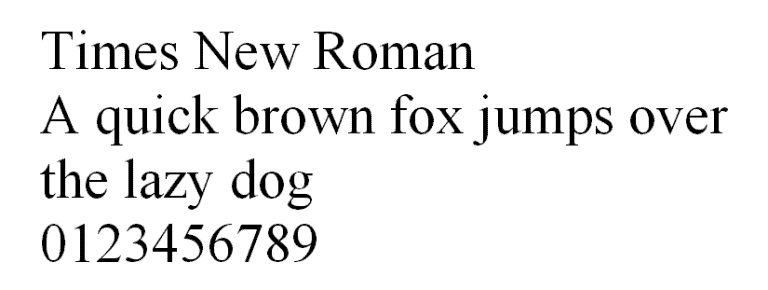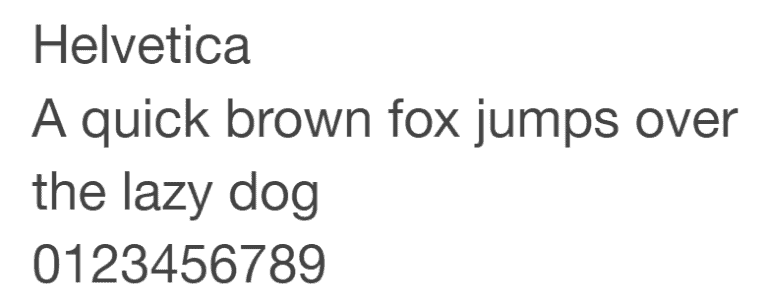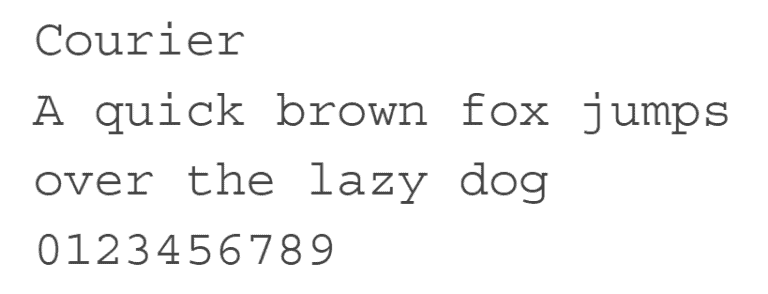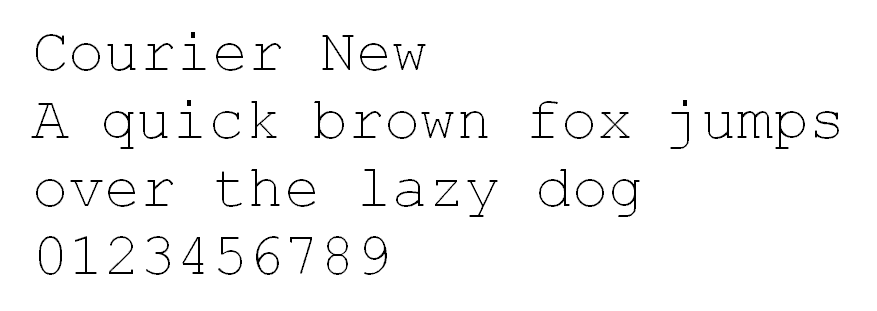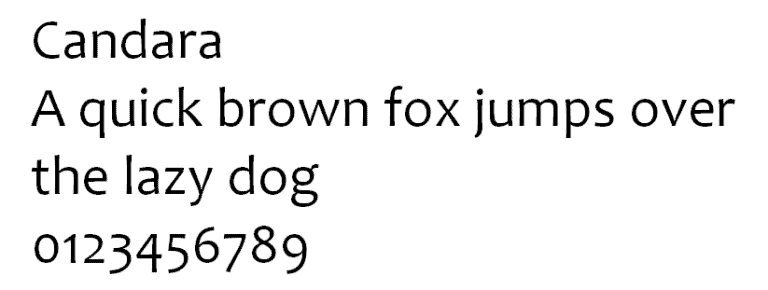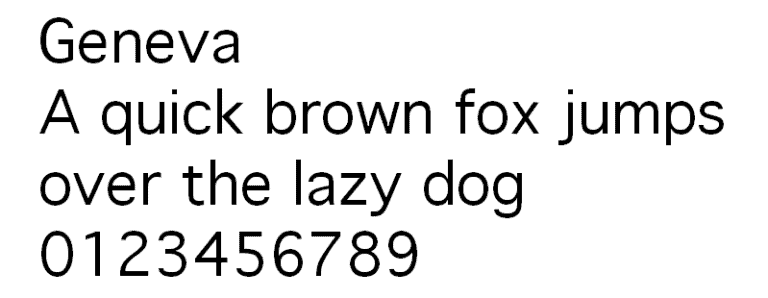
I 20 migliori font HTML da usare nel 2026
I font svolgono un ruolo importante nell’appeal visivo complessivo di un sito web. Un font scelto con cura aiuta a trasmettere il giusto messaggio e a stabilire la coerenza del brand.
A tal fine, un ottimo font per il web deve essere leggibile e sicuro per il web, vale a dire che viene visualizzato bene su diversi dispositivi, browser e sistemi operativi.
Tuttavia, la scelta di un font adatto non è sempre così facile. È frequente imbattersi in font che sono visivamente attraenti ma non sono sicuri per il web o viceversa.
Per aiutarti, abbiamo stilato un elenco dei 20 migliori web font HTML per il tuo sito web.
Cos’è un font web safe
I font web-safe sono font preinstallati nella maggior parte dei sistemi operativi. Questo garantisce che i font vengano visualizzati come previsto quando si accede da diversi dispositivi e browser.
Gli esempi più diffusi di font sicuri per il web sono Arial, Times New Roman ed Helvetica.
Quali sono le categorie di font HTML
In tipografia, ogni font fa parte di una delle cinque famiglie di font, classificate in base alle loro somiglianze di design. Esse sono:
Corsivo
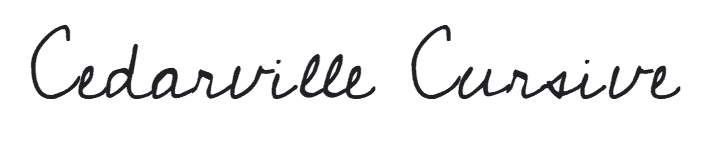
I caratteri corsivi imitano la scrittura a mano, e di solito le lettere sono unite tra loro in modo fluido e inanellato.
Molti associano questo tipo di carattere all’individualità, all’espressione e alla calligrafia. È meglio usare questo tipo di font per le intestazioni, i tagline e i titoli dei post del blog sul tuo sito web, piuttosto che per il testo del corpo. Se usato come font predefinito, il corsivo può essere difficile da leggere.
Fantasy
La famiglia di font Fantasy è generalmente caratterizzata da attributi decorativi presenti su ogni lettera. Molto diffusi tra le opere di narrativa, i caratteri di questo set di font possono aiutare a comunicare istantaneamente il loro genere e a coinvolgere il pubblico.
Ad esempio, questa categoria di font è ampiamente utilizzata nei film fantasy e di fantascienza come Star Wars, Harry Potter e Frozen.
Serif
L’attributo stilistico più importante dei font serif è la presenza di piccoli tratti aggiuntivi ai bordi delle lettere. Inizialmente utilizzato per la stampa a inchiostro, questo stile di font è oggi associato a un senso di formalità ed eleganza.
I siti web utilizzano principalmente serif per il corpo del testo, in quanto è altamente leggibile e aiuta i lettori a scorrere rapidamente i contenuti scritti.
I font serif più diffusi sono Times New Roman, Cambria e Garamond.
Sans-serif
In contrapposizione alla categoria dei font serif, i font sans-serif non presentano tratti aggiuntivi alle lettere.
La maggior parte dei font di questa famiglia presenta larghezze simili e appare moderna e minimalista.
I caratteri sans-serif sono leggibili in qualsiasi dimensione, il che li rende un’ottima scelta sia per la stampa che per l’uso digitale.
Monospace
Ogni lettera e simbolo presente nei font Monospace ha la stessa larghezza.
Poiché i caratteri sono coerenti e facili da distinguere, sono spesso il font predefinito per le macchine da scrivere e i terminali dei computer.
I 20 migliori font HTML sicuri per il web
Di seguito sono riportate 20 opzioni di font HTML sicure per il web che puoi applicare ai tuoi contenuti.
1. Arial
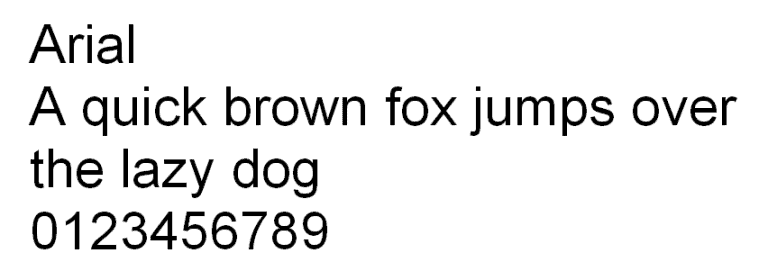
Arial è un font sans-serif versatile e dall’aspetto contemporaneo. Ogni lettera è spessa e robusta, per ottenere un aspetto pulito e minimale.
Arial è stato un font di base per lo schermo grazie alla sua leggibilità in qualsiasi dimensione. Infatti, è il carattere predefinito di Google Docs.
Oltre a ciò, questo font è molto diffuso anche nei media stampati, come giornali e pubblicità.
Nel complesso, se sei alla ricerca di un font classico adatto alla maggior parte dei siti web, Arial è un’ottima scelta.
2. Arial Narrow
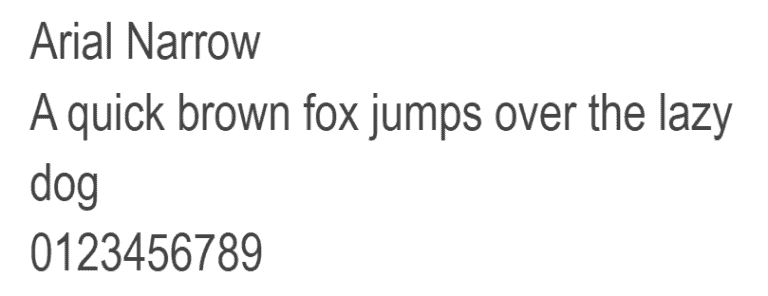
Arial Narrow è uno dei 38 stili della famiglia di font Arial. Rispetto al font originale, questo stile offre un design molto più elegante.
Le lettere appaiono strette e condensate, con poco spazio tra di loro. Questo rende Arial Narrow una scelta ideale per i siti web minimalisti.
Tra le opzioni di abbinamento dei font si possono annoverare i font sans-serif più audaci, come Verdana e Geneva.
3. Times
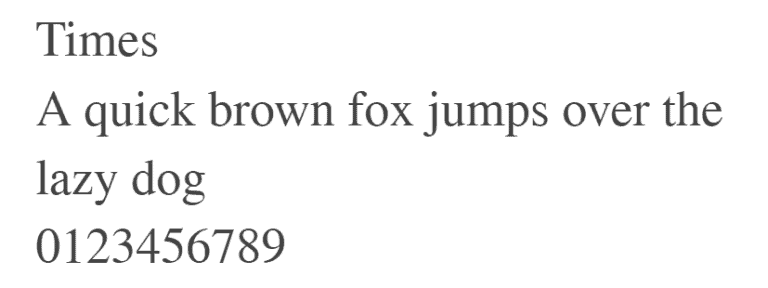
Times è un font serif altamente leggibile grazie al suo contrasto visibile e allo stile condensato.
Il font è noto a tutti perché è presente in diversi media, dai libri alle app di messaggistica, fino ai progetti editoriali commerciali.
In origine, Times era utilizzato principalmente per i media stampati, come i giornali, e da allora è stato associato al giornalismo e alla scrittura accademica.
Pertanto, questo font è la scelta perfetta per creare una sensazione familiare e formale sul tuo sito web.
Inoltre, questo font è adatto a siti web con lunghi blocchi di testo, come le redazioni online e i blog.
- Times New Roman: un’opzione eccellente per i siti web di notizie e di istruzione.
- Cambria: un’opzione versatile, disponibile nelle varianti normale, grassetto, corsivo e grassetto corsivo.
- Monaco: se hai un sito web sul coding o sul gioco, è un ottimo font per i testi decorativi.
Tieni presente che ogni font ha un’impronta unica, quindi assicurati di sceglierne uno che sia leggibile e rappresentativo del tuo brand.